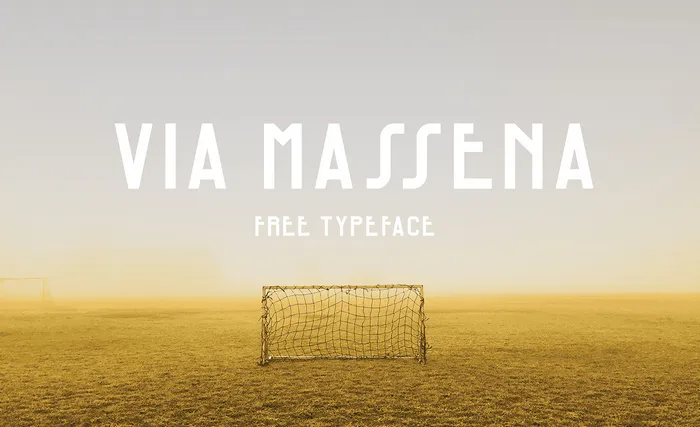
Introduzimos uma nova opção no mundo dos tipografias chamadas Via Massena Typeface. Desenhada pelo experiente designer Edward Sonnex, esta é uma tipografia geometrica e contemporânea, perfeita para qualquer tipo de design gráfico que precise de um olhar atraente e forte. Via Massena Typeface combina a simplicidade geométrica das fontes sans serif com as nuances modernas do display typeface. Ela traz beleza e personalidade aos seus projetos de identidades visuais, sendo uma ótima escolha para logotipos, rótulos e qualquer outro tipo de design gráfico que necessite daquele toque único. Esta tipografia é perfeita para designers que desejam um texto visual moderno e assertivo. Combinando elegância com força, a Via Massena Typeface não se limita apenas às regras convencionais – ela destaca-se em qualquer projeto, tornando o design mais impactante e memorável.